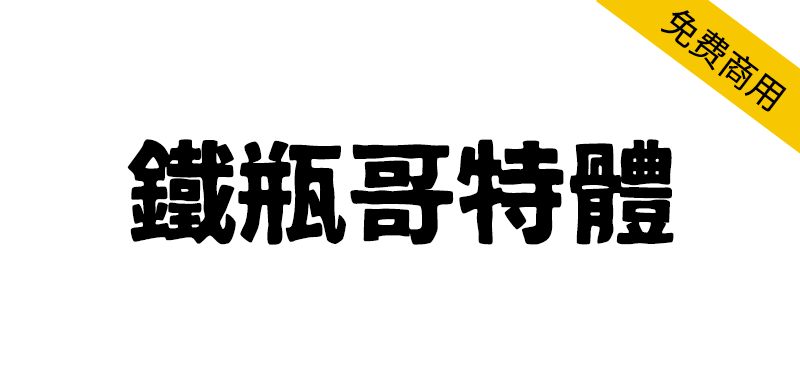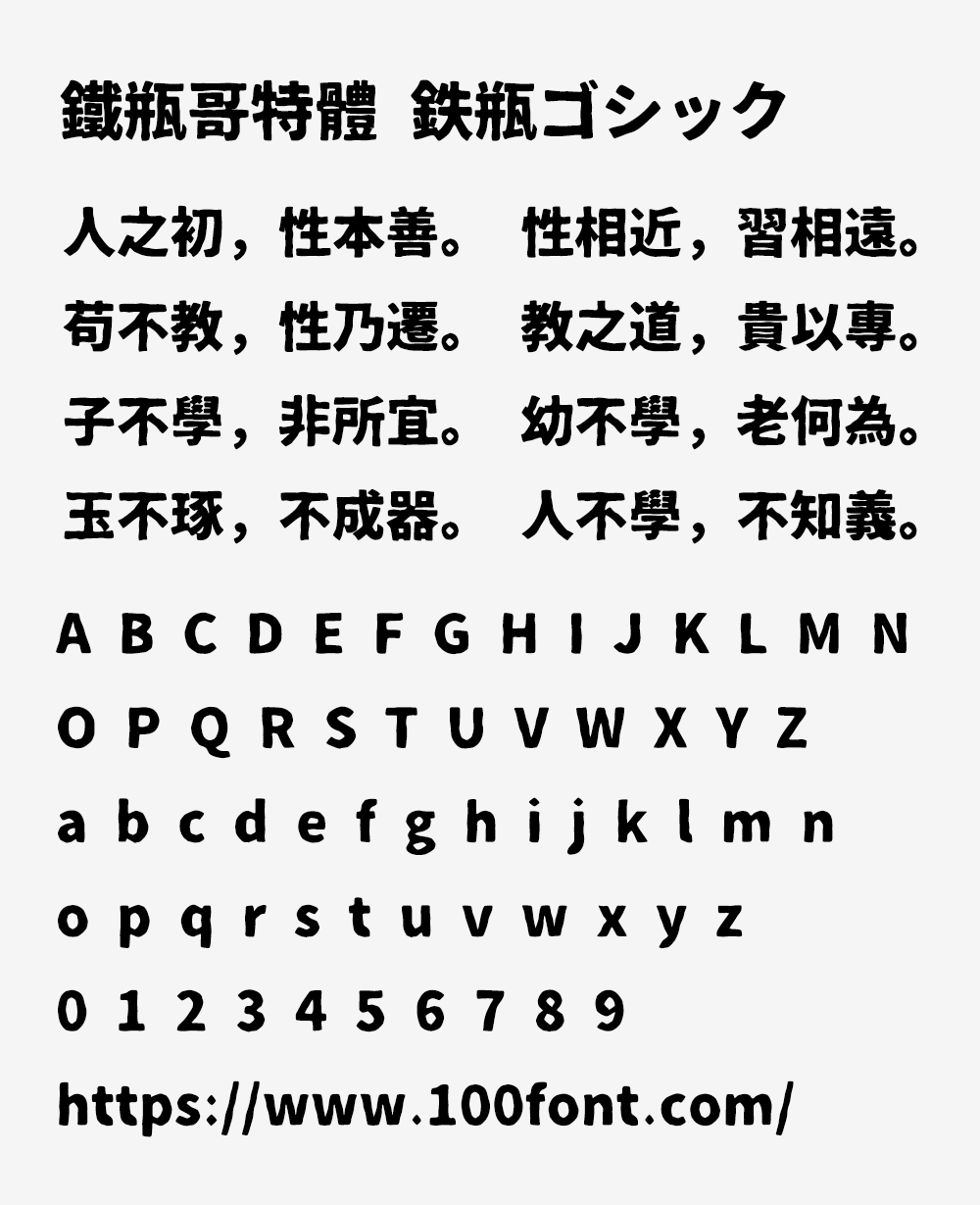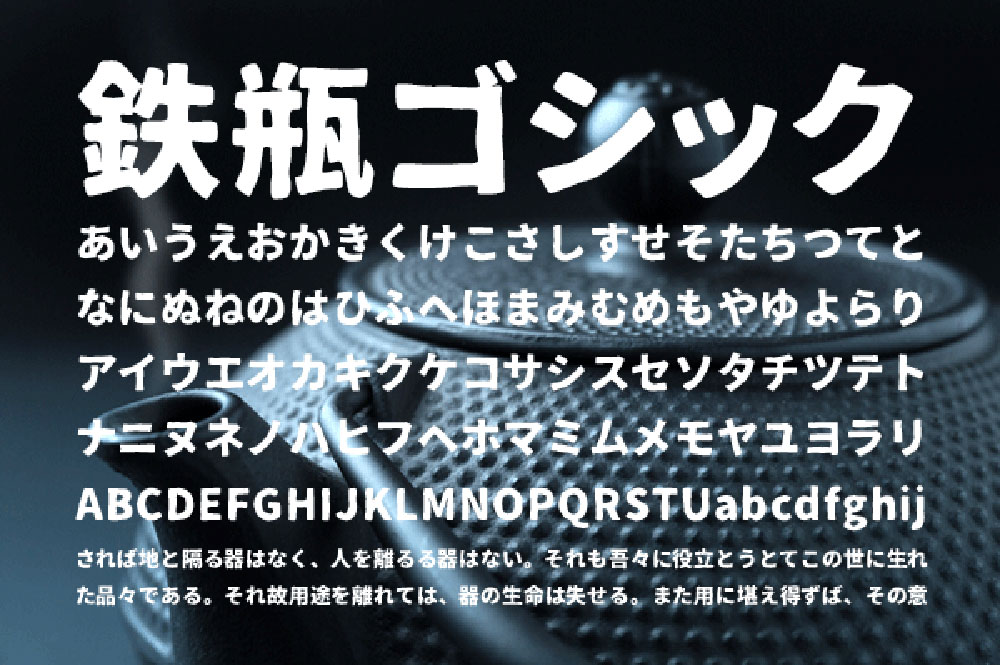
铁瓶黑体(鉄瓶ゴシック)是一款基于日本版思源黑体制作的包含有汉字的日系免费字体,其极粗的笔画和粗犷质感赋予字体独特的韵味,非常适合用于LOGO设计、标题。支持商业和非商业用途,用户可以放心下载使用。(提示:黑体在日语中被称为“哥特体”,宋体在日语中被成为“明朝体”)
フリーフォントの鉄瓶ゴシックは無料でダウンロードできる書体です。また商用・非商用問わず使用可能なので、安心してダウンロードして下さい。ロゴデザインやタイトル、見出し向けの漢字も含まれる日本語フリーフォント。極太のゴツゴツとした質感の味わい深いフォントです。